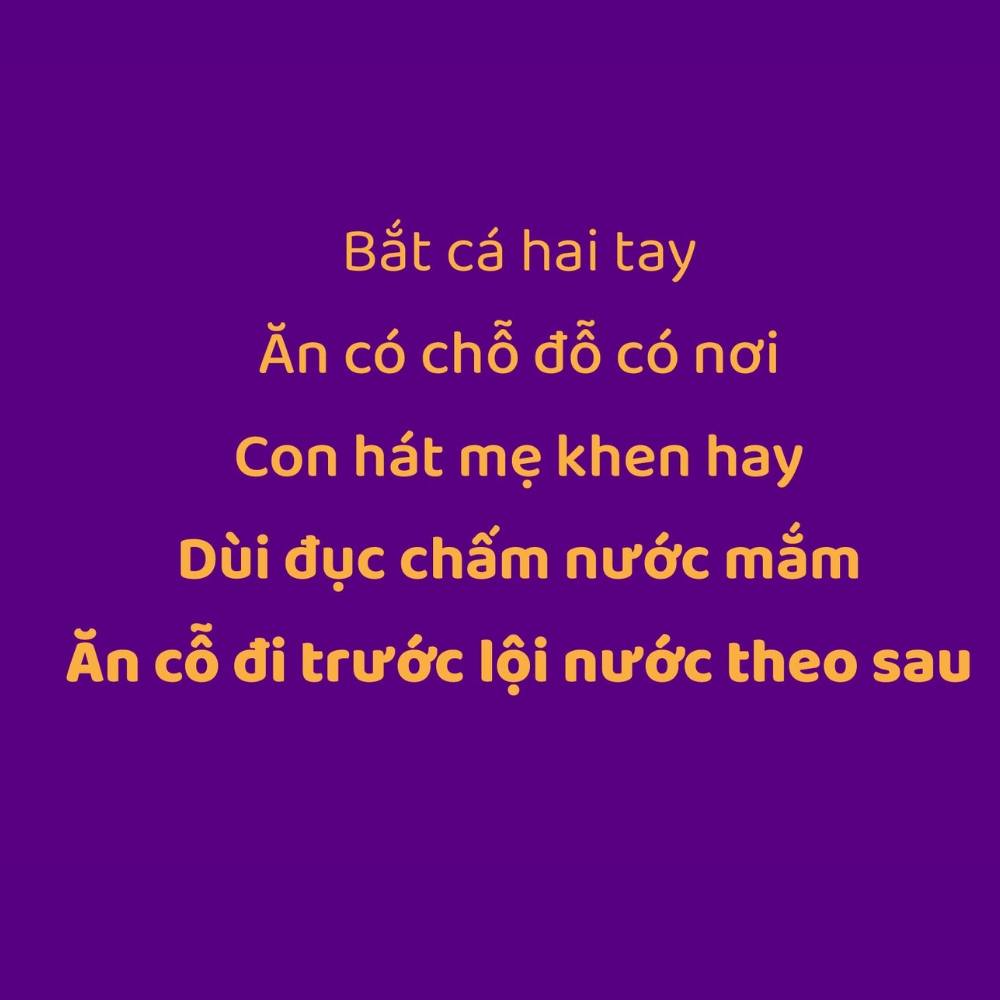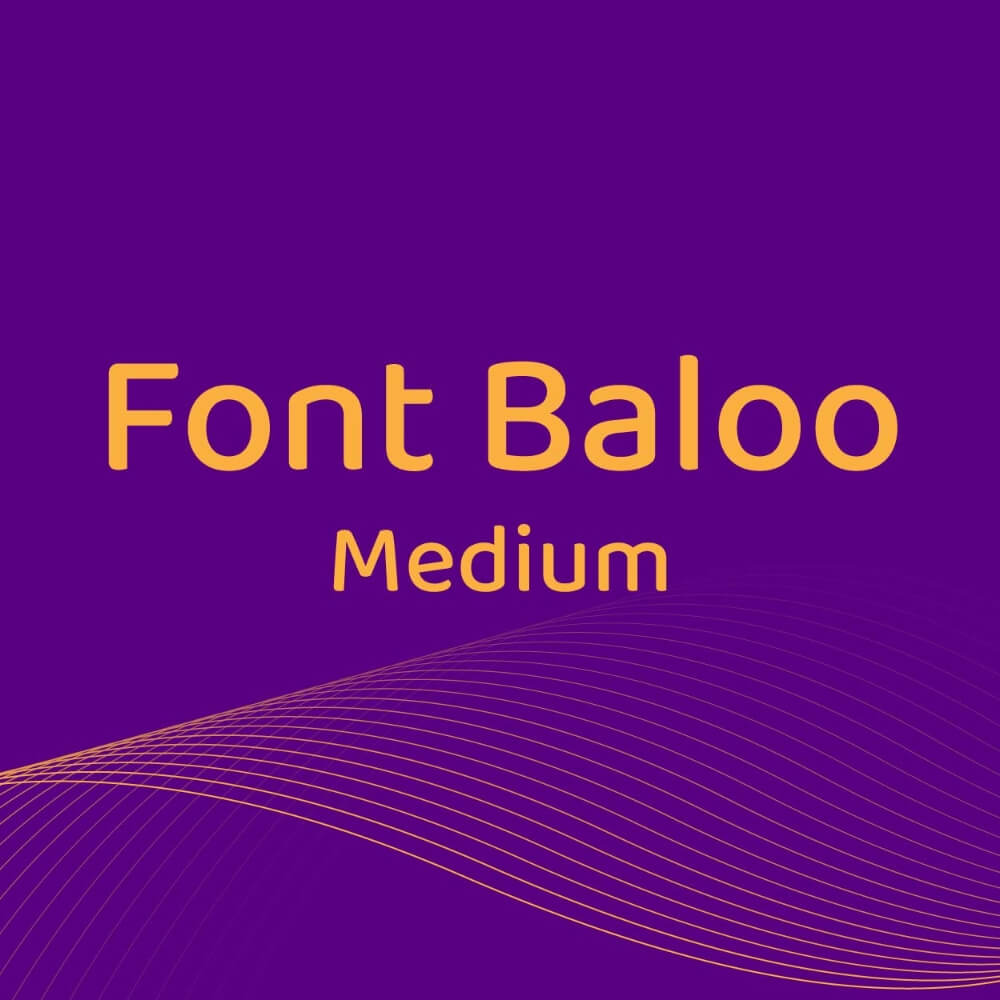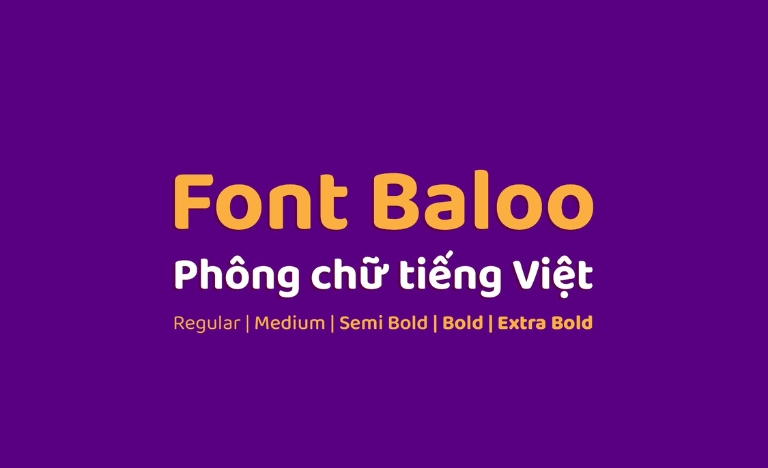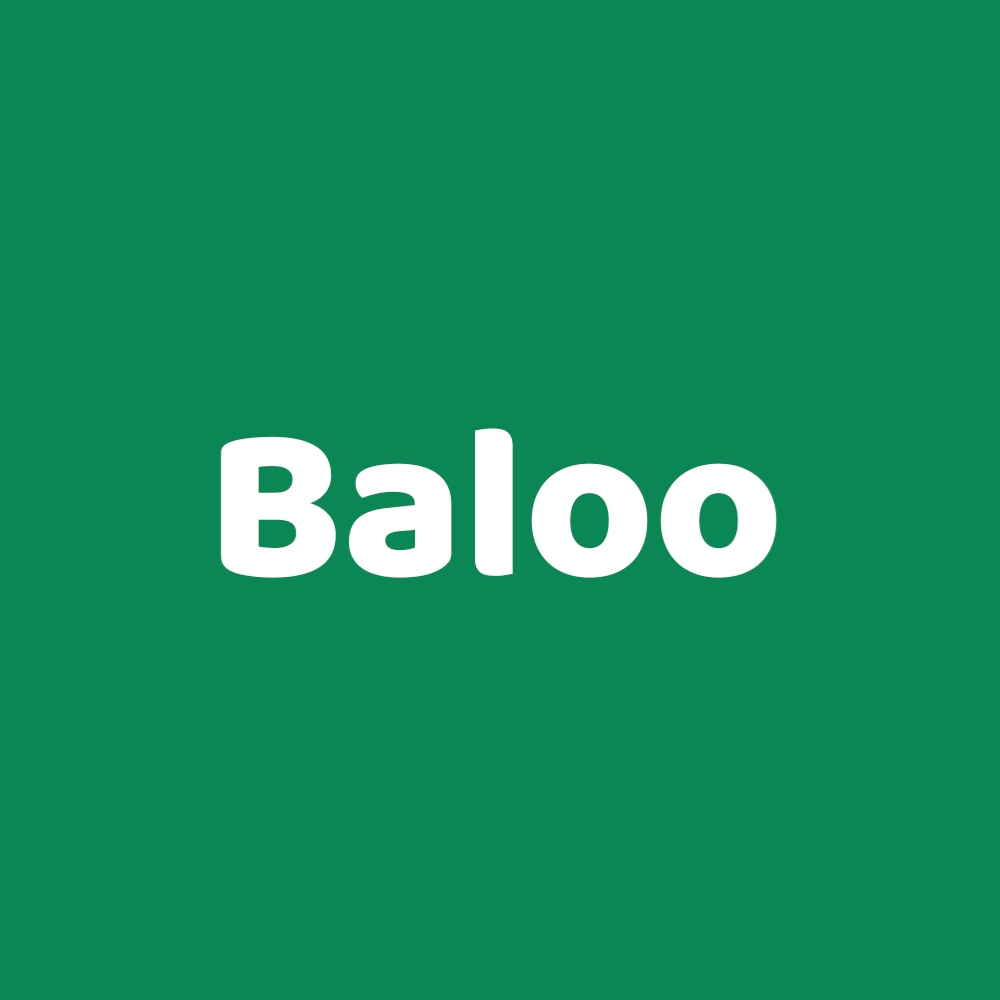
Baloo là một trong những bộ font chữ thuộc dòng Sans-serif nổi tiếng với phong cách bo tròn đầy đặn, mang lại cảm giác thân thiện và vui tươi cho người xem. Sự ra đời của các phiên bản baloo font Việt hóa giúp cộng đồng thiết kế tại Việt Nam có thêm một công cụ trình bày văn bản ổn định, linh hoạt cho cả môi trường in ấn và kỹ thuật số.
Đặc điểm nhận diện của bộ font Baloo Việt hóa
Điểm thu hút của dòng font này nằm ở cấu trúc hình học mềm mại với các góc bo tròn mịn màng, loại bỏ sự khô cứng của các kiểu chữ truyền thống. Font chữ Baloo Việt hóa được tinh chỉnh hệ thống dấu tiếng Việt chuẩn Unicode, giúp các ký tự đặc biệt như “ă, ê, ơ” hay dấu hỏi, ngã được đặt ở vị trí cân đối, duy trì nhịp điệu hình khối của bộ chữ gốc. Điều này mang lại sự mạch lạc và tính thẩm mỹ cao cho văn bản, ngay cả khi trình bày ở các tiêu đề có kích thước lớn.
Sự ổn định của Baloo còn thể hiện qua khả năng hiển thị rõ nét trên nhiều loại màn hình khác nhau. Nhờ chiều cao ký tự (x-height) lớn và khoảng cách giữa các chữ cái thông thoáng, Baloo giúp người đọc dễ dàng tiếp nhận thông tin mà không bị mỏi mắt. Đây là phương án phù hợp cho những ai muốn tìm kiếm sự giao thoa giữa tính hiện đại, năng động và sự gần gũi cho thương hiệu hoặc dự án kiến trúc của mình.
| Phân loại phong cách | Rounded Sans-serif / Modern Style |
| Nhóm kiểu chữ | Baloo, Baloo 2, Baloo Bhai… |
| Mục đích phù hợp | Tiêu đề, Poster, Logo, Branding công trình |
Tư vấn trình bày: Baloo có nét chữ khá dày và đậm. Để bản thiết kế đạt được sự cân bằng thị giác, bạn nên phối hợp Baloo cho phần tiêu đề chính và sử dụng một font chữ không chân mảnh hơn cho phần nội dung mô tả chi tiết, giúp bố cục thông tin trở nên khoa học và chuyên nghiệp hơn.
03 Ứng dụng mẫu Baloo font Việt hóa trong thực tế
Nhờ vẻ ngoài giàu năng lượng và tính ứng dụng cao, bộ font này mang lại giá trị thực tế khi được đưa vào các hạng mục trang trí và nhận diện không gian:
- Bảng nhận diện cho Homestay và Khu vui chơi: Những nét chữ tròn trịa của Baloo rất ăn ý khi xuất hiện trên chất liệu mica, gỗ hoặc alu màu sắc tại các khu nhà lắp ghép nghỉ dưỡng. Font chữ này giúp không gian toát lên vẻ trẻ trung và thân thiện đối với du khách.
- Thiết kế bao bì quà tặng và văn phòng phẩm: Sử dụng mẫu Baloo font Việt hóa cho các nhãn dán, thiệp mời giúp thương hiệu tạo được ấn tượng về sự chuyên nghiệp nhưng vẫn giữ được nét tinh tế, tận tâm đối với khách hàng.
- Trang trí không gian nội thất sáng tạo: Bạn có thể dùng font Baloo để cắt chữ nổi hoặc in tranh decor tại phòng khách, phòng trẻ em trong các căn hộ hiện đại nhằm tạo điểm nhấn đầy thẩm mỹ và vui tươi cho không gian sống.
03 Lưu ý kỹ thuật khi trình bày bố cục với Baloo 2 font Việt hóa
Để khai thác hiệu quả vẻ đẹp của dòng font bo tròn này mà không làm rối mắt người xem, người thiết kế nên lưu tâm một số kinh nghiệm sau:
- Hạn chế viết hoa toàn bộ ký tự: Cấu trúc của Baloo được thiết kế tối ưu nhất cho kiểu viết chữ thường kết hợp hoa đầu dòng. Việc viết hoa toàn bộ cụm từ có thể làm văn bản trông nặng nề và giảm khả năng nhận diện mặt chữ nhanh.
- Kiểm soát khoảng cách giữa các chữ: Do các nét chữ bo tròn chiếm diện tích chiều ngang khá lớn, bạn nên nới rộng khoảng cách chữ một chút khi hiển thị ở kích thước nhỏ để tránh hiện tượng bết dính nét.
- Lựa chọn màu sắc rực rỡ: Font Baloo phát huy hiệu quả thị giác tốt khi phối cùng các tông màu nóng, màu pastel hoặc phối đa sắc, giúp tôn vinh tinh thần năng động và hiện đại của bộ chữ.